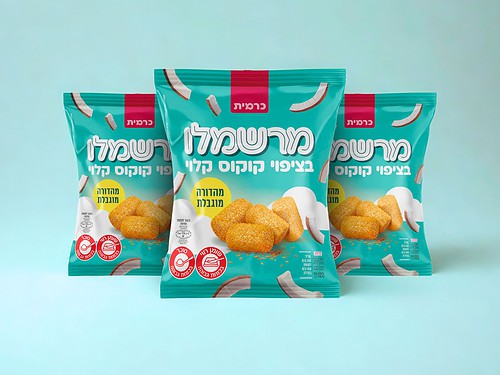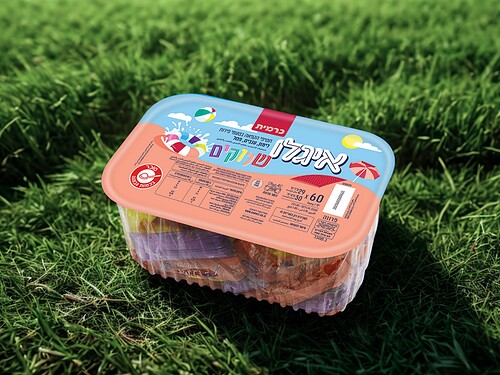
על אודות פונט פלוני מעוגל
גרסה מעוגלת וחברותית לפונט פלוני הפופולארי. הקצוות המעוגלים בשילוב עם צורות־האות הגיאומטריות הופכים אותו ללבבי ומאיר פנים. הוא לוטש בקפידה ועובד מצויין במגוון משקליו גם בכותרות וגם כטקסט־רץ – למראה צעיר, נעים וידידותי להפליא.
פלוני מעוגל מכיל 1,113 תווים, המון OpenType™ Features ותמיכה מלאה באנגלית, רוסית ועוד 228 שפות לטיניות וקיריליות, ועל כן מדובר בפונט אידיאלי לשימוש באותיות עבריות לצד אנגלית.
המלצת שימוש לפי משקל
לייט לכותרות בגודל 22 px/pt ומעלה. לא לטקסט רץ
רגיל, בינוני, דמי־בולד ובולד לכותרות וגם לטקסט־רץ
אולטרה־בולד לכותרות ולוגואים -
OpenType Features
- Small capitals אבג 123 Abc ← אבג 123 Abc
- ליגטורות סטנדרטיות Office ← Office
- fi fl ffi ffl ff
- ליגטורות סודיות History ← History
- AVOCADO ← AVOCADO
- אשכרה ← אשכרה
- כאן ← כאן
- ניקוד מדוקדק קֳ ← קֳ
- מספרים רגילים 1,234,567.89%
- ⏎ Smallcaps (לעברית) 1,234,567.89%
- ⏎ OldStyle Figures 1,234,567.89%
- ⏎ Tabular Figures 1,234,567.89%
- שברים, מוֹנֶה וְמְכַנֶּה 1/2 ← 1/2
- 123/456 ← 123/456
- חלופות הקשריות רכבת ← רכבת
- eggs ← eggs
- אותיות רחבות ﬡﬢﬣﬤﬥﬦﬧﬨ
- חלופות סגנוניות ע ← ע
- a ← a
- g ← g
- y ← y
- % ← %
- 0 ← 0
- 1 ← 1
- וריאציות נטויות AQUA
- סוואשים אופציונליים AQUA
- ₪ בגבהים שונים ₪ ₪ ₪ ₪
- סמלים מיוחדים ואורנמנטים: ◌⇓↯✱☯☺☑❝⇱§❡¶™
- ⏎ סמלי מטבע $€£¥₪¢¤ƒ₹₽₩₺Ł♦฿
- ⏎ סימני מקלדת ⌘⌥⇧⇞✲⏎⎀⇪⌫^
- ⏎ חיצים ↑↗→↘↓↙←↖↕↔
- ⏎ יחידות מידה 12kΩ 8°C №69 ℮90g 1·5ℓ
- ⏎ סימנים מתמטיים ∅‱≥∞∫∏∑√µ∂≠¬±≈
- ⏎ אייקונים גיאומטריים ★♥●■▲☆♡○□△◊⬢⬠